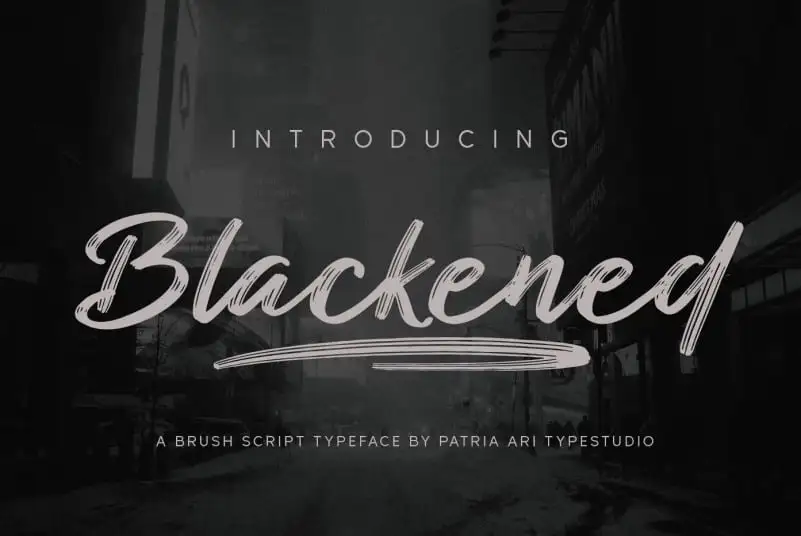
Blackened Brush Font – Fonte Grátis
Blackened Brush Font
A Blackened Brush Font é uma tipografia brushscript que traz nuances multilíngues além de suavizações sofisticadas. Desenvolvida pelo Patria Ari Typestudio, esta fonte apresenta um estilo elegante e versátil, perfeita para designers gráficos em busca de uma personalização única. Seja você criando rótulos de embalagens impactantes ou trabalhando em design editorial, a Blackened Brush Font é uma escolha certeira. Com sua tipografia brushscript multifuncional e suas suavizações que adicionam um toque refinado à escrita, esta fonte atende a todas as necessidades dos criativos. Através de seu design fluido e vibrante, ela oferece o ideal para criar designs em linha com os padrões atuais da moda gráfica.